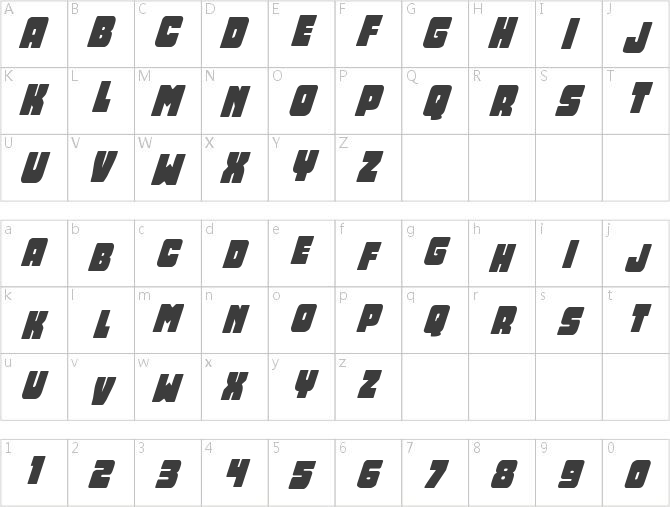
Opus Mundi Super-Italic
Opus Mundi Super-Italic介紹
Opus Mundi Super-Italic字體字庫是一款讓人賞心悅目、百看不厭的英文字體,適合各類廣告和產品包裝設計應用,字體大小0.05MB,格式為ttf字體,上傳用戶是@小咖,作者/版權方為未知